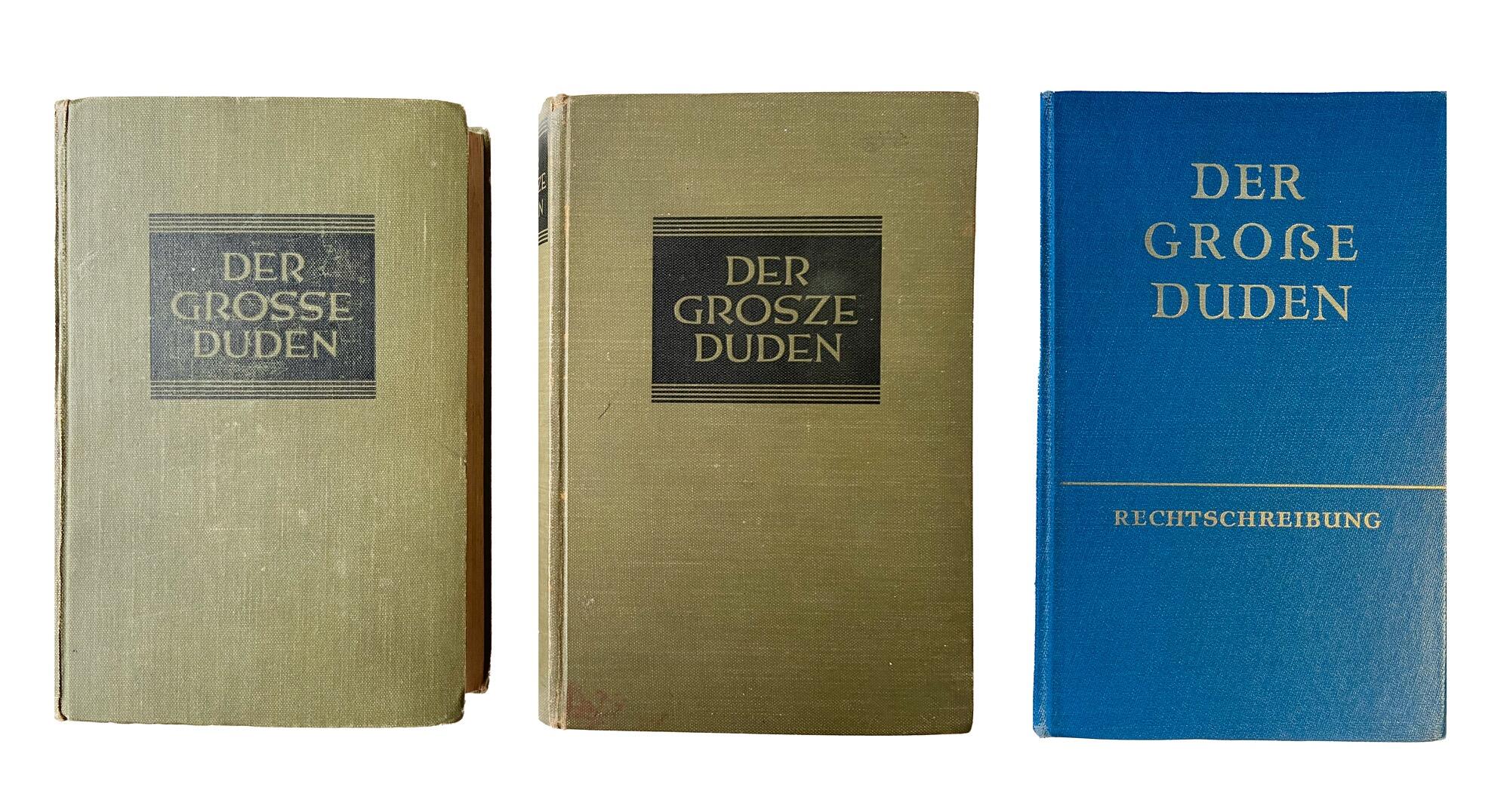
Das Versal-Eszett bezeichnet die Großbuchstabenform des Buchstaben ß (Eszett). Die Erweiterung des deutschen Alphabets um diesen Buchstabens wird seit Ende des 19. Jahrhundert diskutiert. Bis 1941 waren in Deutschland die gebrochenen Schriften für deutsche Texte vorherrschend und in diesen Schriften gibt es nur in sehr seltenen Fällen Großschreibung von Wörtern. Das ß existierte deswegen lange Zeit nur als Kleinbuchstabe, da es für eine Großbuchstabenvariante schlicht keinen Bedarf gab. Seit dem Schriften-Erlass von 1941 und der damit verordneten Einführung der Antiquaschrift als Normalschrift in Deutschland ist die Großschreibweise von deutschen Wörtern aber wieder – wie überall wo lateinische Schrift benutzt wird – häufig anzutreffen. Sobald nun deutschsprachiger Text in Kapitälchen oder Versalien ausgezeichnet wird, fehlt die entsprechende Großbuchstabenvariante.
Beispiele:
- Meißner → MEI?NER
- groß → GRO?
Großschreibweise des ß
Der Bedarf nach einem Großbuchstaben für »ß« wurde also schon sehr früh angemeldet, beispielhaft sei aus der neunten Auflage des Rechtschreibdudens aus dem Jahre 1925 zitiert:
»Für ß wird in großer Schrift SZ angewandt, z.B. MASZE (Maße) – aber MASSE (Masse), STRASZE, PREUSZEN, MEISZNER, VOSZ. Die Verwendung zweier Buchstaben für einen Laut ist nur ein Notbehelf, der aufhören muss, sobald ein geeigneter Druckbuchstabe für das große ß geschaffen ist.«
Nach der Rechtschreibreform von 1996 ist bei Großschreibung SZ nicht mehr zulässig. Da es immer weniger benutzt wurde, ist es nun durch die zwei Einzelbuchstaben SS zu ersetzen.
»Weiß« wird laut amtlicher deutscher Rechtschreibung in Deutschland und Österreich im Versalsatz als »WEISS« geschrieben. Die Verwechslungsgefahr, besonders bei Eigennamen hat sich dadurch noch vergrößert.
- Weiß → WEISS → Weiss oder Weiß?
Aber auch die frühere Schreibung mit SZ hilft nur bedingt, da man auch bei dieser nicht weiß, ob die zwei Buchstaben S und Z nun für die Einzelbuchstaben s und z oder für ß stehen sollen.
- KNEISZ → Kneisz oder Kneiß?
Der Eindeutigkeit halber ist man bei behördlichen Dokumenten dazu übergangen, »ß« auch bei der Großbuchstabenschreibung beizubehalten, also z.B. »GROßMANN« für »Großmann« zu schreiben. Dieser Mischsatz aus Groß- und Kleinbuchstaben wird seit den 1980er Jahren bei deutschen Reisepässen und Personalausweisen angewandt. Auch die Deutsche Post – wie auch die Finanzämter – empfehlen, beim Ausfüllen von Formularen in Großbuchstaben den Kleinbuchstaben ß beizubehalten.
Seit der Rechtschreibreform von 1996 besteht zudem zusätzlich das Problem, dass die Unterscheidung von ß und ss nun eine lautliche Funktion bekommen hat.
- Kuss (kurzer Vokal)
- Gruß (langer Vokal)
Im Versalsatz wird dieses Prinzip jedoch außer Kraft gesetzt, wenn das ß durch Doppel-S ersetzt wird.
- Gruß → GRUSS
Mit einem großen Eszett kann sowohl das Problem der Eigennamen, als auch das Problem der Aussprache behoben.
- Meißner → MEIẞNER → Meißner
- Maße → MAẞE (jeweils eindeutig lang ausgesprochener Vokal, statt unklare Aussprache und Bedeutung bei MASSE)
![]()
Zwei Duden aus dem Jahr 1929, die noch mit Ersatzschreibungen für das ß arbeiten. Rechts: DDR-Duden aus dem Jahr 1957 mit einem extra für das Cover gezeichnetem, großem Eszett.
Verschiedene Schriftkünstler haben ihre Schriften seit Anfang des 20. Jahrhunderts mit einem Versal-Eszett ausgestattet. Seit Anfang des 21. Jahrhunderts und der Unicode-Kodierung (siehe nächster Abschnitt) nimmt die Zahl (auch internationaler) Schriftveröffentlichungen mit Eszett immer weiter zu.
Kodierungsbestrebungen
- Im Jahr 2004 beantragte der Typograf Andreas Stötzner beim Unicode Consortium die Aufnahme eines Latin Capital Letter Double S in den Unicode. Der Antrag wurde verworfen, da unter anderem die Existenz dieses Buchstabens nicht ausreichend bewiesen war.
- Im Jahr 2005 zeigte der Interessensverband Rat für deutsche Rechtschreibung e.V. auf Nachfrage Verständnis, eine Abhilfe für die notdürftige Ersetzung durch SS zu schaffen. Es bedürfe allerdings »einer Initiative aus der Schreibgemeinschaft (z.B. von Seiten der Typografen)«, und nicht der Iniative des Rates für deutsche Rechtschreibung.
- Ein zweiter Antrag auf eine Aufnahme des Versal-Eszetts als LATIN CAPITAL LETTER SHARP S ist am 27. April 2007 vom Komitee des zuständigen Deutsches Institut für Normung (DIN) gestellt worden. Deutschland wurde in der einwöchigen, turnusmäßigen Sitzung durch Mitglieder des DIN-NIA 29.01 (Codierte Zeichensätze) vertreten. Im Rahmen der 50. Sitzung der zuständigen Internationalen Organisation für Normung (ISO) bzw. der International Electrotechnical Commission (IEC)-Working-Group vom 23. bis 27. April 2007 ist beschlossen worden, das Versal-Eszett solle gemäß diesem Vorschlag im Unicode-Standard die Stelle U+1E9E erhalten.
- Am 4. April 2008 ist wie angekündigt mit dem Erscheinen des Unicode-Standards Version 5.1 das große Eszett aufgenommen worden und hat den Platz U+1E9E erhalten.
Technisches
- Glyphe: ẞ
- Unicode: U+1E9E
- Unicode-Bezeichnung: LATIN CAPITAL LETTER SHARP S
Rechtschreibung
Seit 2017 ist das große Eszett Teil der amtlichen deutschen Rechtschreibung. Die Schreibung von Wörtern mit großem Eszett wurde als Variante neben der Ersatzschreibung Doppel-S geführt, also STRASSE oder STRAẞE.
In der Überarbeitung von 2024 wurde die Formulierung noch einmal abgeändert. Die Schreibung mit ẞ kann nun als Hauptform angesehen werden und die Schreibung mit Doppel-S wird als mögliche Variante angegeben.